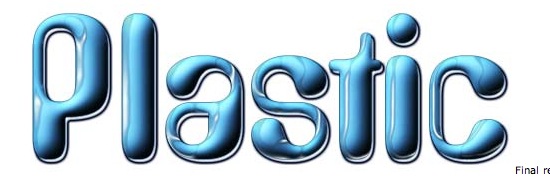
Það á stundum ágætlega við að leika sér með að setja áferð á letur með Photoshop. Eins getur það verið verulega hallærislegt á köflum.
Hvað sem því líður langar mig að benda á ágætis stökkpall, samansafn af greinum um hvernig er hægt að setja mismunandi áferð á letur. Það besta í þessu er að vel flestar aðferðirnar kenna manni ýmsar brellur í Photoshop sem maður vissi kannski ekkert um. Það er því alveg þess virði að prófa bara til að læra.